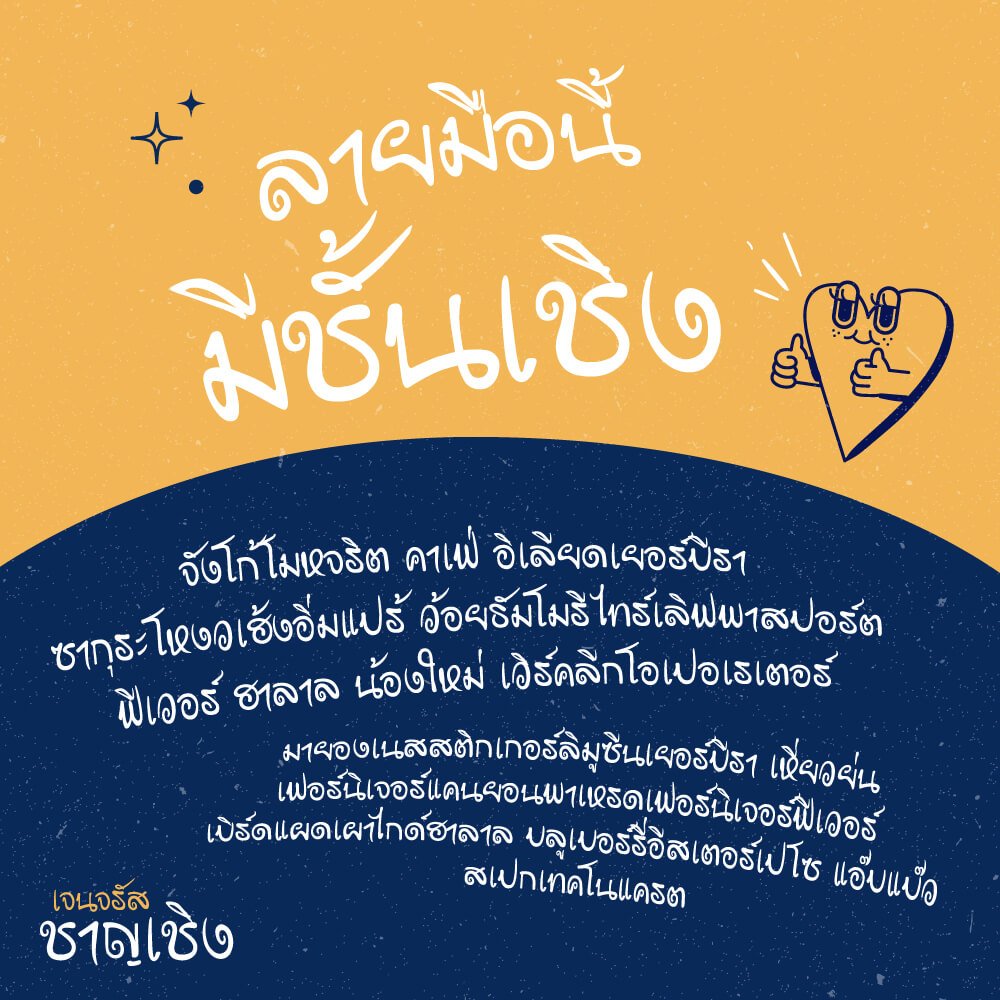
เจนจรัส ชาญเชิง (Jenjrus ChanCherng)
ฟอนต์เจนจรัส ชาญเชิง เป็นฟอนต์ลายมือ ซึ่งดัดแปลงจากเวอร์ชันปกติ มีชั้นเชิงลูกเล่นมาจากภาพประกอบ ลายเส้นการ์ตูนสมัยก่อนผสมกับลายมือคุณพ่อ ฟีลลิ่งสนุกๆ มันส์ๆ เหมาะกับเป็นหัวข้อหรือทำป้ายและสื่อโฆษณาต่างๆ
ฟอนต์นี้เป็นผลงาน ชุดที่ 8 ของคุณพ่อ อายุ 77 ปี ที่รักการออกแบบฟอนต์เป็นงานอดิเรกครับ